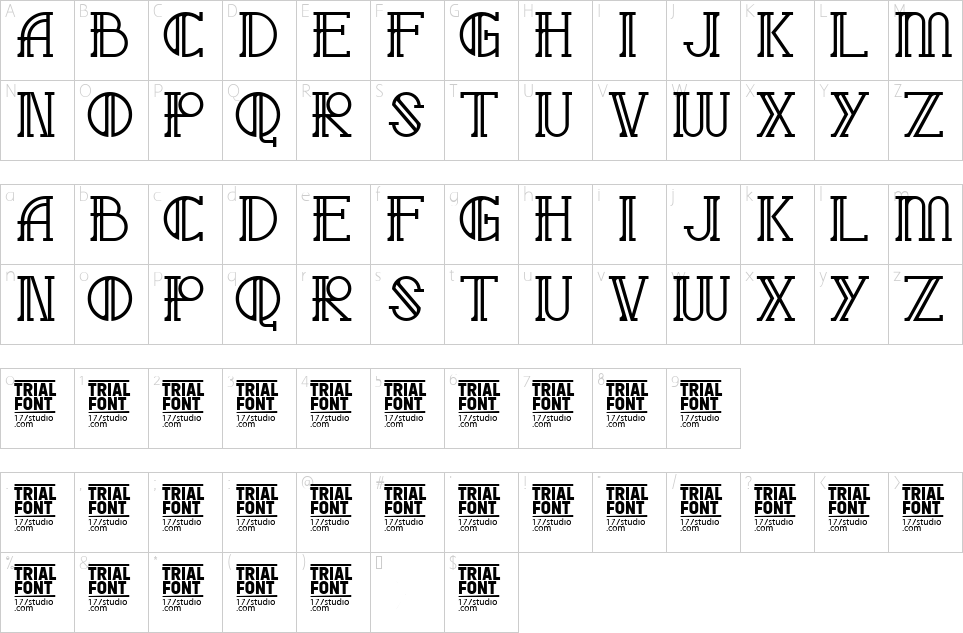
Modern Fashion é uma fonte de caracteres moderna e elegante, perfeita para estilos de design gráfico contemporâneos. Desenvolvida pelo designer desconhecido, Modern Fashion foi projetada com características clean e fáceis de ler, tornando-a ideal para rótulos de produtos de moda, grafismos de redes sociais, logotipos de marcas e design de layout de sites. Com seu estilo minimalista e arredondado, Modern Fashion oferece uma experiência de leitura confortável e atraente para qualquer projeto de design. Esta fonte foi baixada 359 vezes e está disponível gratuitamente para todos os usuários. Instale e experimente agora para dar um toque único e moderno aos seus projetos de design.